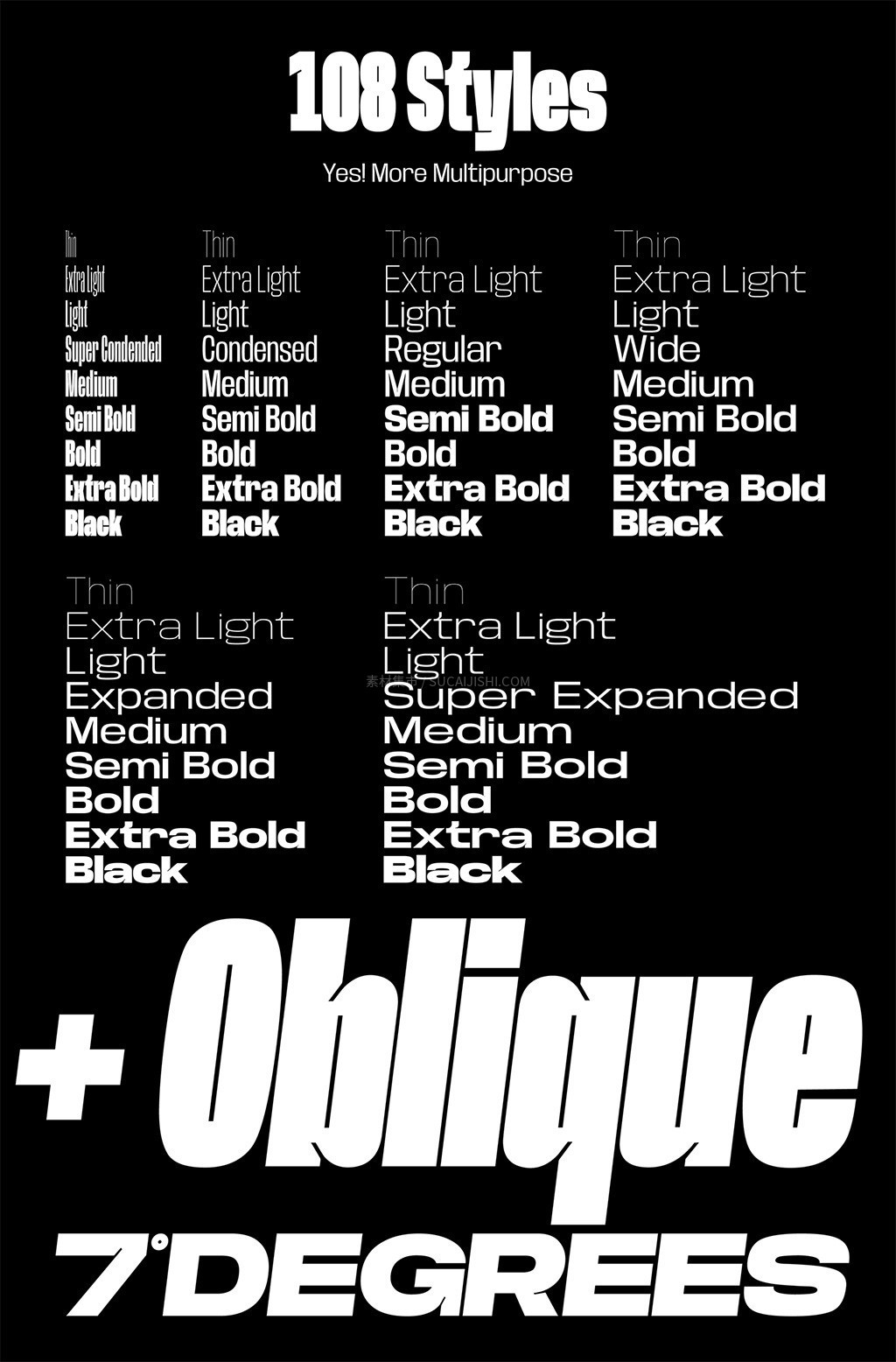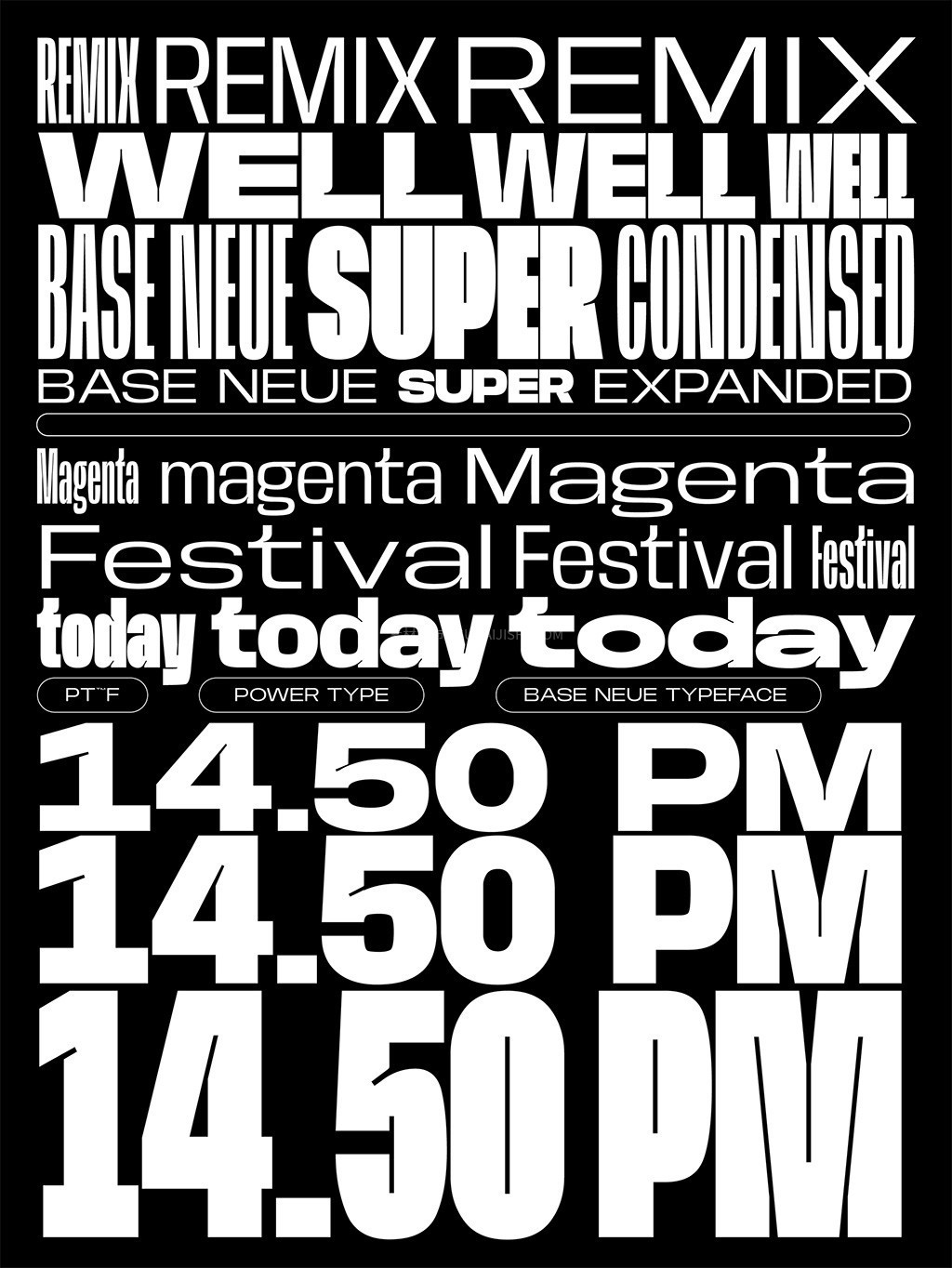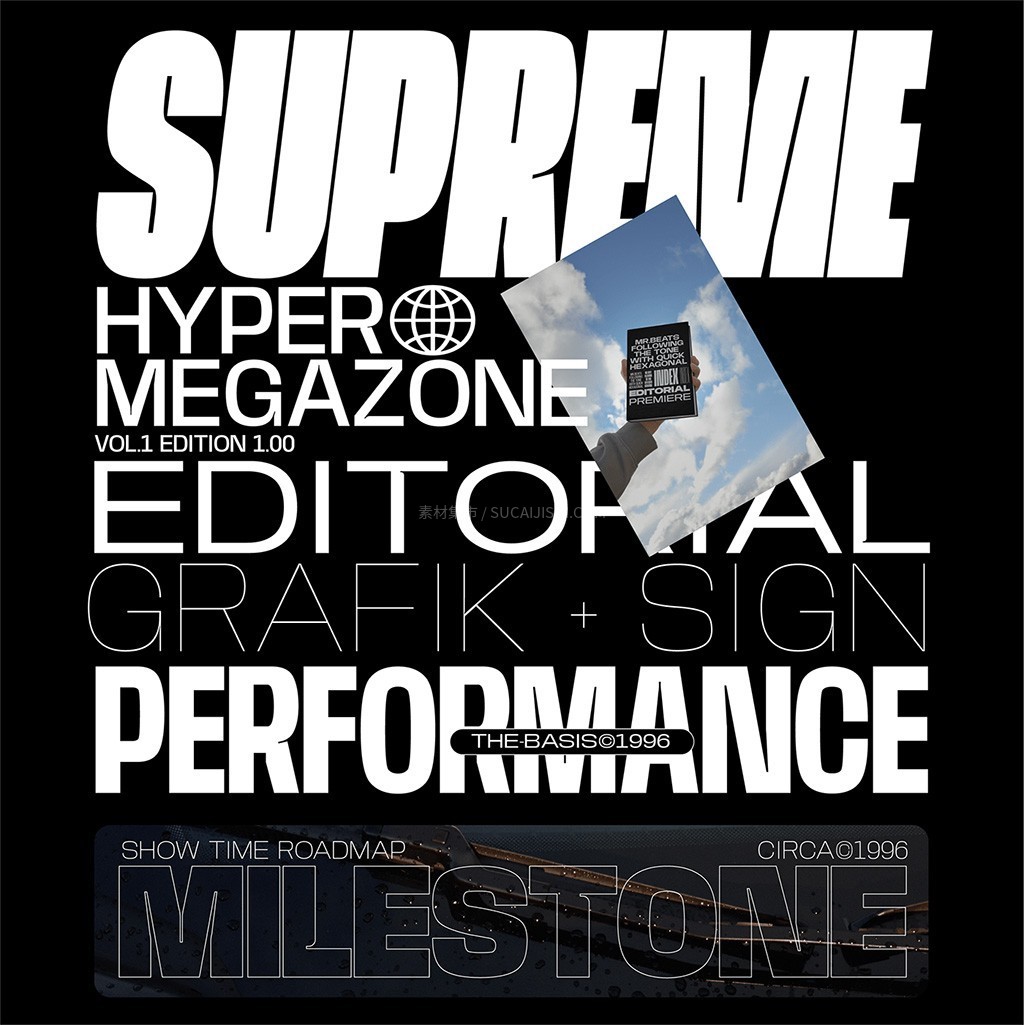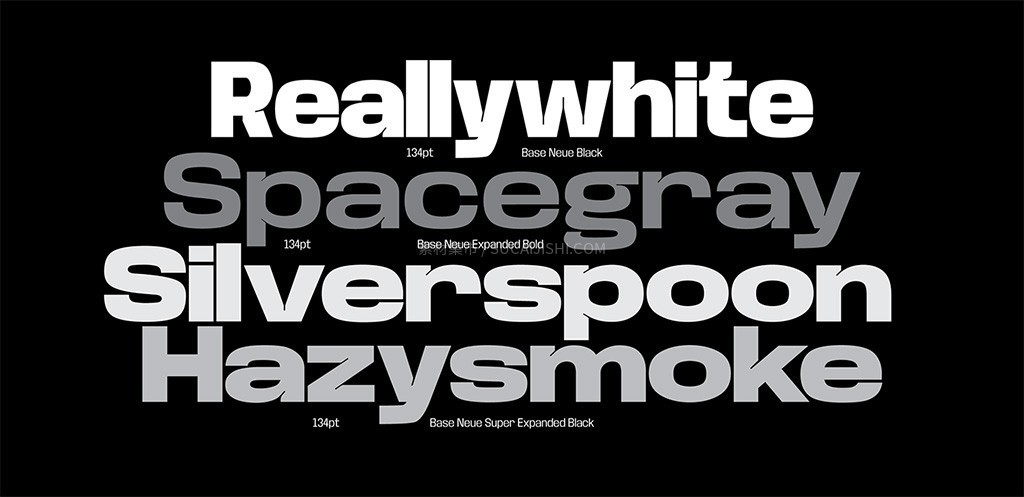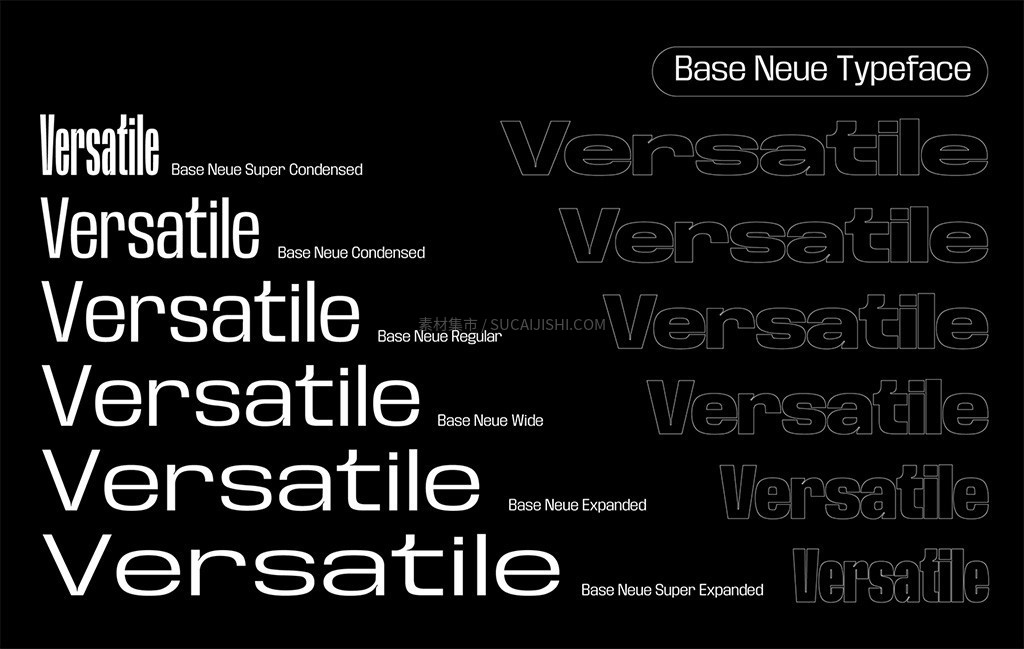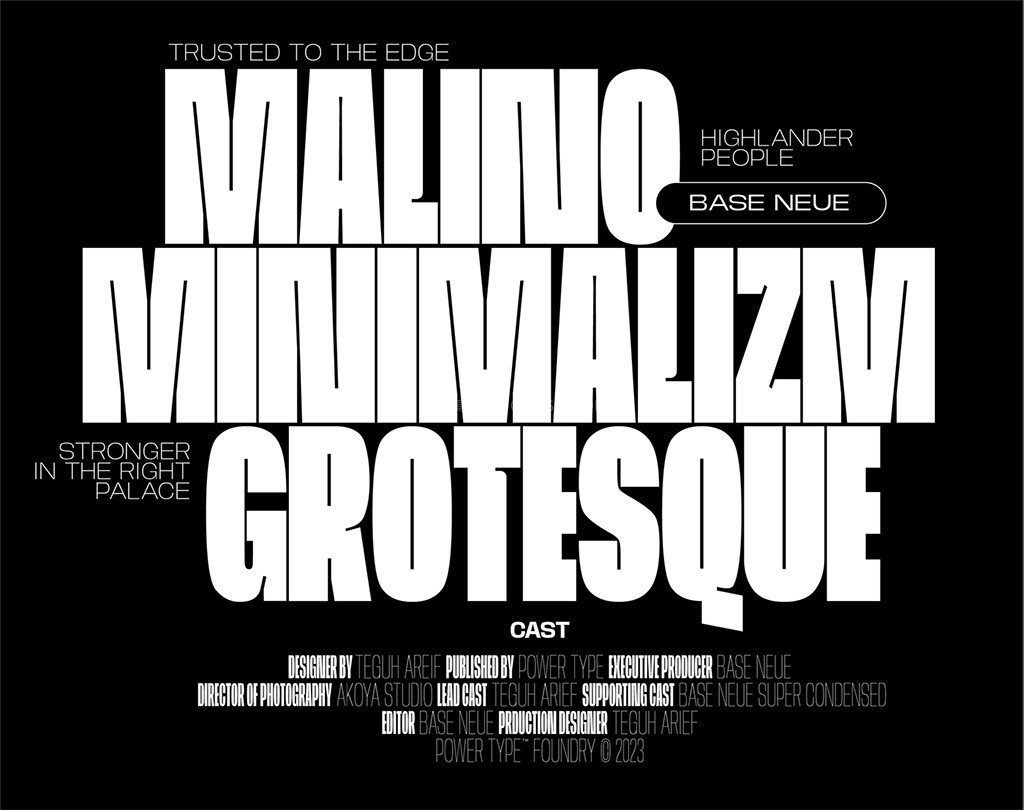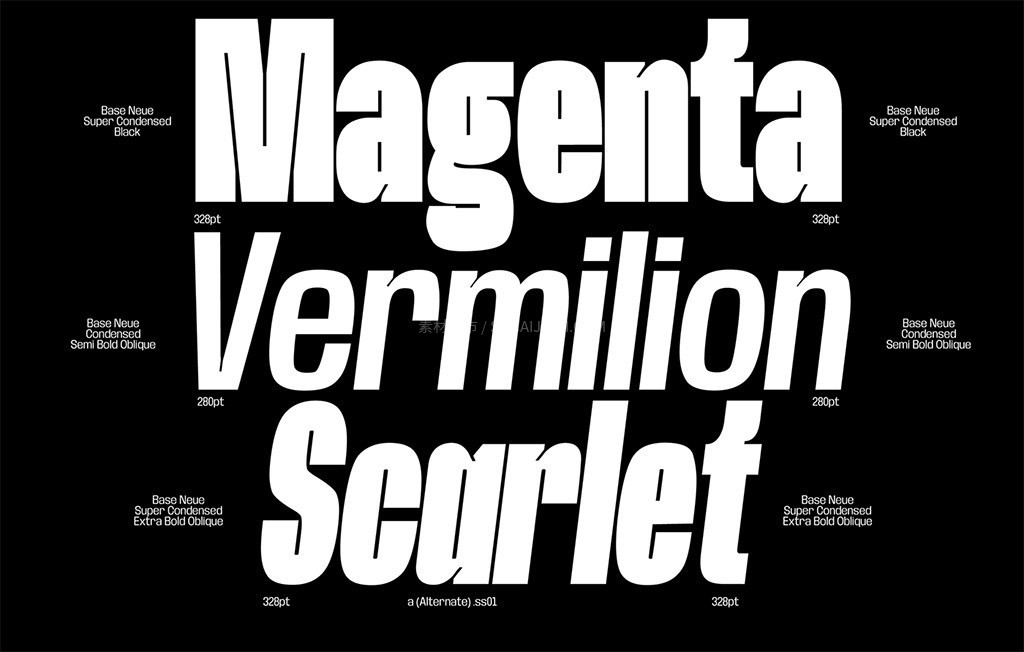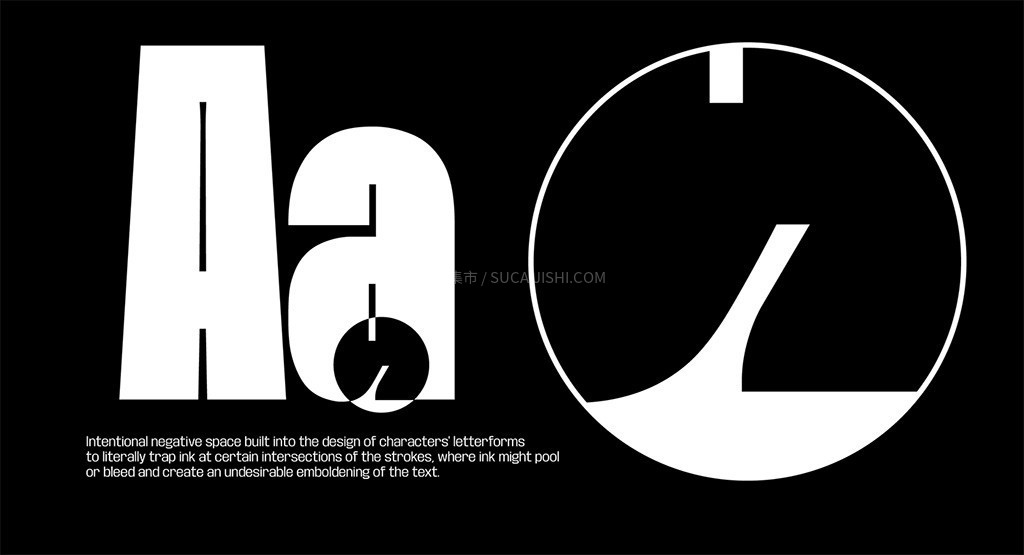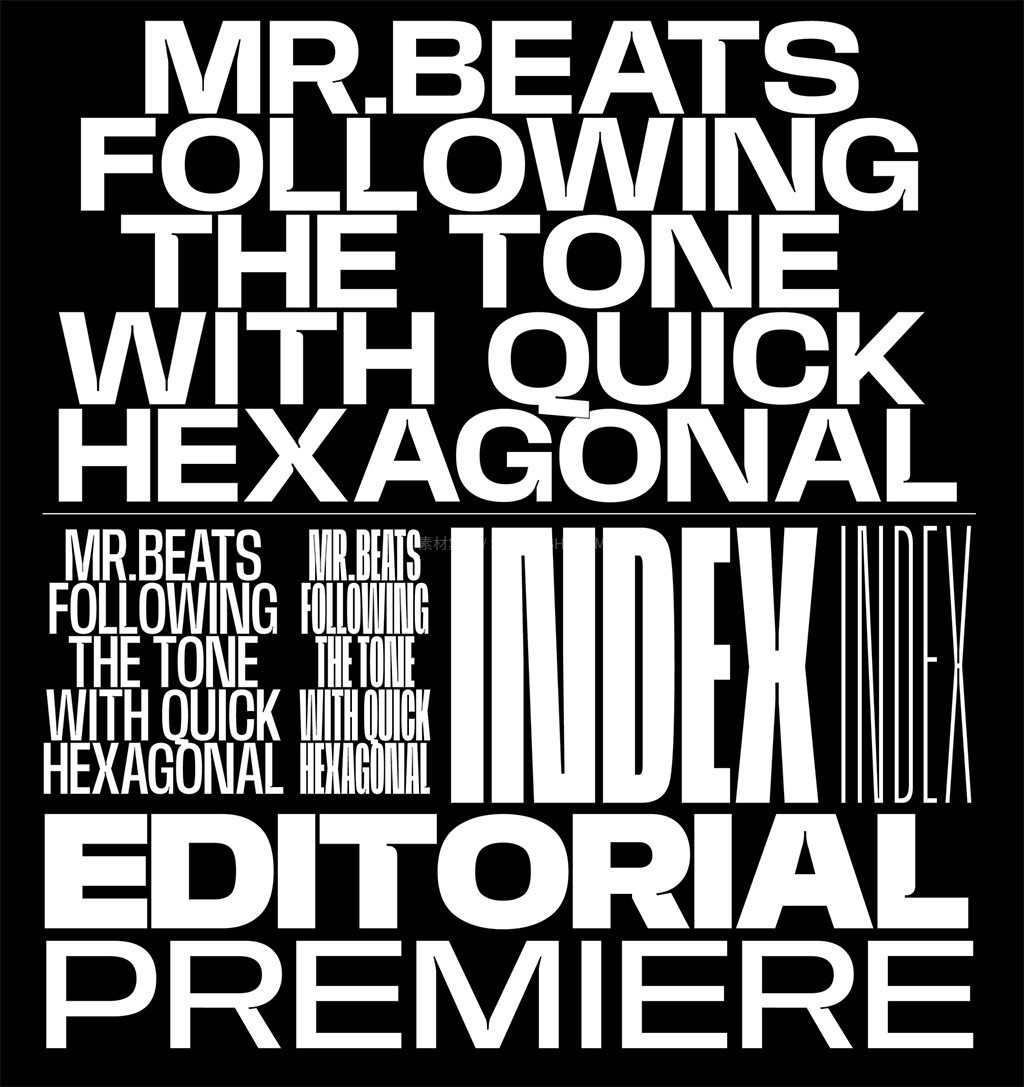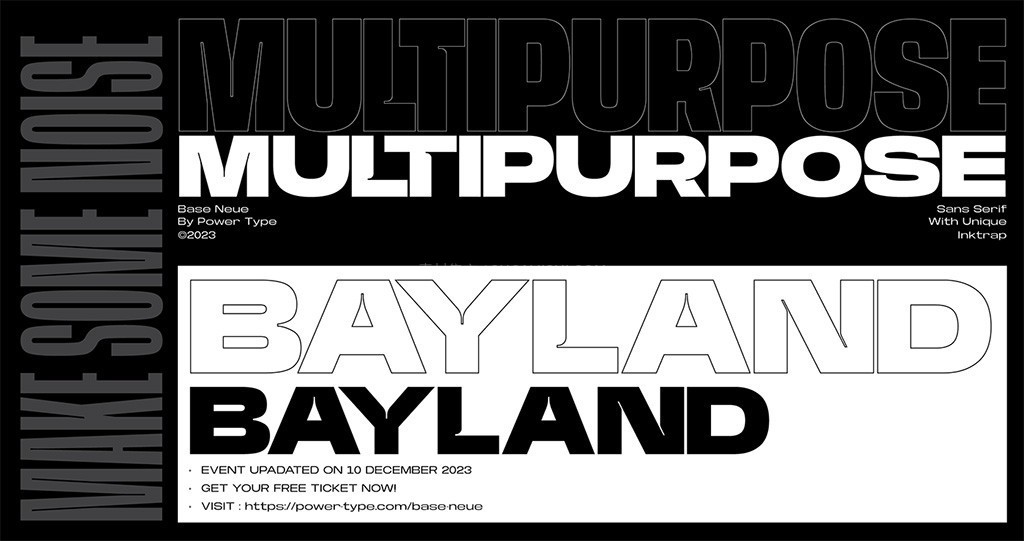
Base Neue完整版:现代极简无衬线英文字体家族
这是一款由 Power Type™ Foundry 发行的现代系统化无衬线英文字体家族。Base Neue 融合了极简主义美学与精妙的墨坑(Ink Trap)细节,无论是极小字号的屏幕显示,还是巨幅海报的醒目排版,它都能提供极致的清晰度与专业的高级质感,是现代视觉设计中不可或缺的全能排版利器。
Base Neue完整版:现代极简无衬线英文字体家族支持 97+ 种语言,每款样式约 782 glyphs (字形),包含替代字形、Ligatures 连字功能,同时提供 Variable 可变字体版本。它涵盖了从 Compressed 到 Expanded 的 6 种字宽,以及从 Thin 到 Black 的 9 种字重。